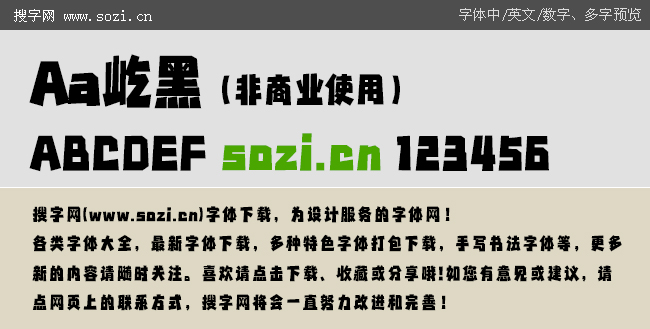
Aa屹黑
搜字網(wǎng)給大家提供一款A(yù)a屹黑(非商業(yè)使用)中文字體下載,Aa屹黑是一款藝術(shù)黑體字體,字體簡潔有力,字形飽滿端正,充滿力量,具有很好的視覺感,適合應(yīng)用于藝術(shù)設(shè)計(jì)、平面宣傳設(shè)計(jì)、網(wǎng)頁設(shè)計(jì)、海報(bào)設(shè)計(jì)等應(yīng)用(此字體為個(gè)人非商用版,商用可以聯(lián)系QQ:1006760504)。